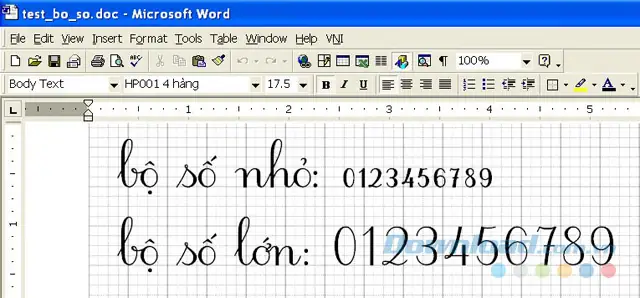
Font chữ tập viết đẹp dành cho bậc tiểu học là công cụ hỗ trợ đắc lực giúp các em học sinh làm quen với việc viết chữ chuẩn, đẹp từ những bài tập đầu tiên. Việc sử dụng các font viết tay phù hợp không chỉ giúp học sinh rèn luyện thói quen viết đúng, viết đẹp mà còn tạo hứng thú trong quá trình học tập. Trên internet hiện nay có rất nhiều font chữ viết tay dành cho học sinh tiểu học, tuy nhiên không phải font nào cũng đảm bảo được sự chuẩn xác về độ cao, khoảng cách, nét chữ phù hợp với chương trình giáo dục. Bài viết này sẽ cung cấp cho thầy cô, phụ huynh và các bạn học sinh danh sách các font chữ tập viết đẹp dành cho bậc tiểu học được kiểm định chất lượng, cùng với link tải miễn phí tốc độ cao và hướng dẫn cài đặt chi tiết.
Giới thiệu các font chữ tập viết đẹp dành cho bậc tiểu học
Font chữ tập viết là loại font được thiết kế mô phỏng theo nét chữ viết tay của học sinh, với đặc điểm là các nét thanh đậm rõ ràng, độ cao chuẩn theo vở ô ly, khoảng cách giữa các chữ vừa phải. Việc sử dụng font chữ tập viết đẹp dành cho bậc tiểu học giúp học sinh dễ dàng làm quen với việc trình bày bài viết, luyện viết đúng mẫu chữ quy định. Các font chữ viết tay cho học sinh tiểu học thường được chia thành hai nhóm chính: font chữ viết thường (chữ in) và font chữ viết hoa (chữ in hoa). Mỗi nhóm lại có nhiều kiểu khác nhau như font chữ viết nghiêng, font chữ viết thẳng, font chữ viết nét đậm, font chữ viết nét thanh.
Các font chữ tập viết đẹp dành cho bậc tiểu học phổ biến nhất hiện nay
Font ABC Cheri
Font ABC Cheri là một trong những font chữ viết tay được ưa chuộng nhất dành cho học sinh tiểu học. Font này có thiết kế nét chữ mềm mại, tròn trịa, tạo cảm giác dễ viết, dễ đọc cho các em học sinh. ABC Cheri phù hợp để in bài tập, đề kiểm tra, hay các tài liệu học tập cần nét chữ viết tay. Ưu điểm nổi bật của font ABC Cheri là kích thước chữ vừa phải, độ cao chuẩn, khoảng cách giữa các chữ đều, giúp học sinh dễ dàng luyện viết theo mẫu. Font này cũng được sử dụng phổ biến trong các tài liệu giáo dục, sách tham khảo, và các bài giảng điện tử.
Font Thư Pháp Tiểu Học
Font Thư Pháp Tiểu Học là lựa chọn lý tưởng cho những ai muốn tìm kiếm một font chữ tập viết đẹp dành cho bậc tiểu học mang phong cách nghệ thuật. Font này được thiết kế với nét chữ cách điệu, thanh thoát, giúp học sinh phát triển thị hiếu thẩm mỹ trong việc写字. Tuy nhiên, do đặc thù của font thư pháp, giáo viên và phụ huynh nên sử dụng font này một cách hợp lý, chủ yếu trong các hoạt động ngoại khóa, thi vẽ chữ đẹp, hoặc trang trí bài viết. Font Thư Pháp Tiểu Học không phù hợp để in bài tập chính khóa vì có thể gây khó khăn cho học sinh trong việc nhận diện chữ cái.
Font Cheri Line
Font Cheri Line là biến thể của font ABC Cheri, với đặc điểm là các nét chữ được cách điệu bằng các đường kẻ mảnh ở đầu và cuối nét bút. Điều này tạo nên sự khác biệt và hấp dẫn cho font chữ, đồng thời vẫn giữ được sự dễ đọc, dễ viết. Font Cheri Line đặc biệt phù hợp để in tiêu đề, đề mục, hoặc các chữ cái lớn trong tài liệu học tập. Khi sử dụng font Cheri Line, giáo viên có thể tạo ra những bài giảng sinh động, thu hút sự chú ý của học sinh.
Font VNI-ThuThao
Font VNI-ThuThao là một trong những font chữ viết tay truyền thống, được sử dụng rộng rãi trong hệ thống giáo dục Việt Nam. Font này có ưu điểm là nét chữ rõ ràng, độ cao chuẩn, khoảng cách đều, rất phù hợp để luyện viết cho học sinh tiểu học. Font VNI-ThuThao được tích hợp sẵn trong bộ font VNI, một bộ font phổ biến và quen thuộc với nhiều thế hệ học sinh. Tuy nhiên, do được thiết kế từ lâu, font VNI-ThuThao có phần cứng nhắc hơn so với các font mới ra đời. Dù vậy, đây vẫn là một lựa chọn đáng tin cậy cho những ai muốn tìm kiếm một font chữ tập viết đẹp dành cho bậc tiểu học theo phong cách truyền thống.
Font VNI-Van
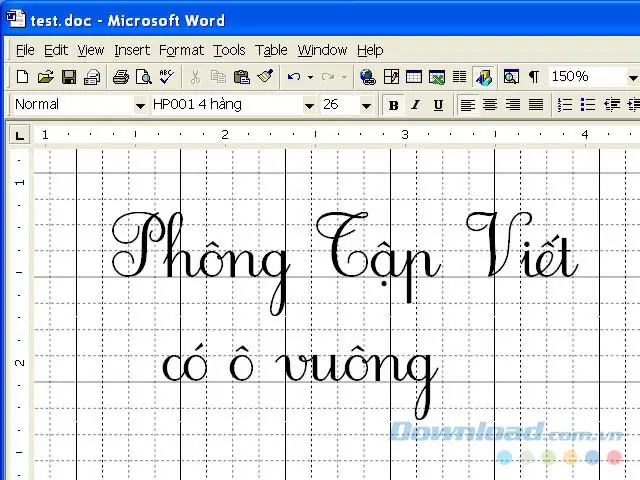
Font VNI-Van là một font chữ viết tay khác trong bộ font VNI, có nét chữ thanh mảnh, nhẹ nhàng hơn so với font VNI-ThuThao. Font này phù hợp với các em học sinh có khả năng viết chữ đẹp, muốn luyện viết theo phong cách thanh thoát, uyển chuyển. Font VNI-Van cũng được sử dụng khá phổ biến trong các tài liệu in ấn, đặc biệt là các bài viết, thơ văn, hoặc các đoạn trích dẫn cần nét chữ mềm mại. Tuy nhiên, do nét chữ mảnh, font VNI-Van không phù hợp để in với cỡ chữ quá nhỏ, vì có thể gây khó đọc.
Lời kết
Font chữ tập viết đẹp dành cho bậc tiểu học là công cụ hỗ trợ đắc lực trong quá trình dạy và học. Việc lựa chọn và sử dụng font chữ phù hợp không chỉ giúp học sinh rèn luyện kỹ năng viết chữ mà còn góp phần phát triển thị hiếu thẩm mỹ, tạo hứng thú trong học tập. Hy vọng rằng với danh sách các font chữ được giới thiệu trong bài viết, cùng với hướng dẫn tải và cài đặt chi tiết, thầy cô, phụ huynh và các bạn học sinh sẽ tìm được font chữ phù hợp nhất cho nhu cầu của mình. Hãy truy cập summerland để khám phá thêm nhiều tài nguyên hữu ích khác nhé!